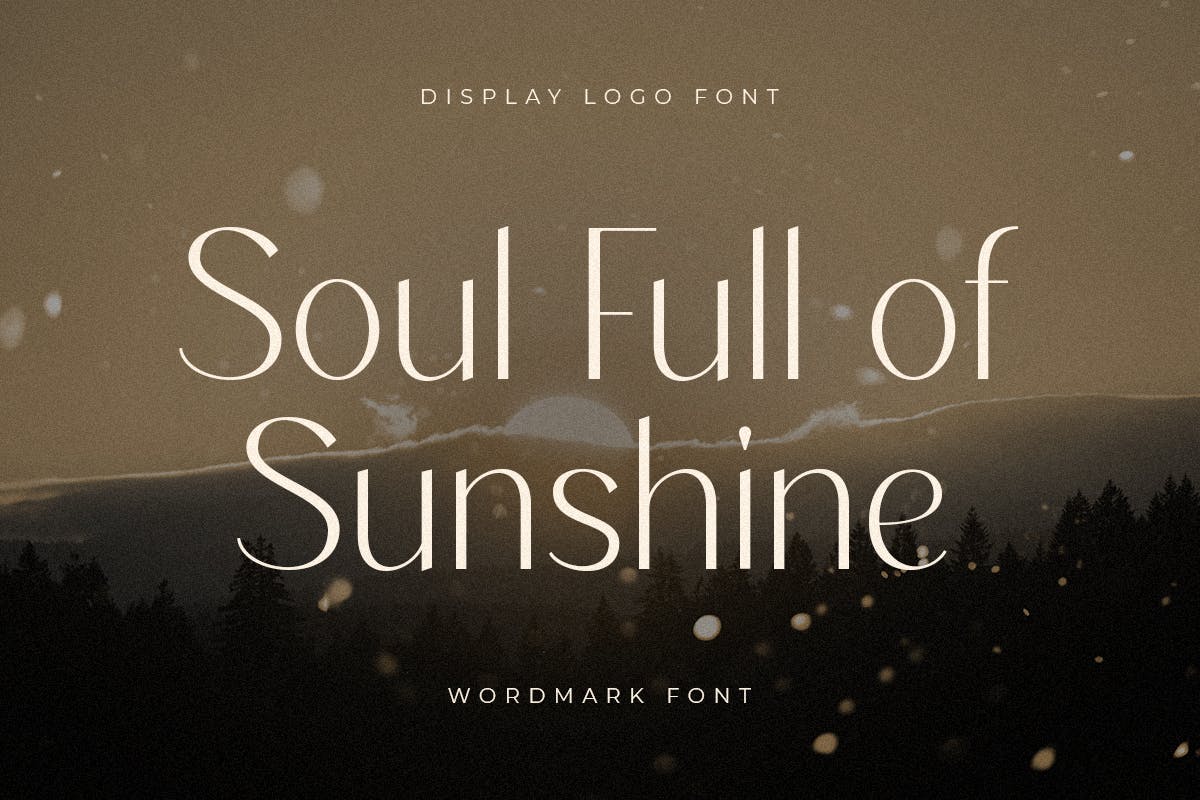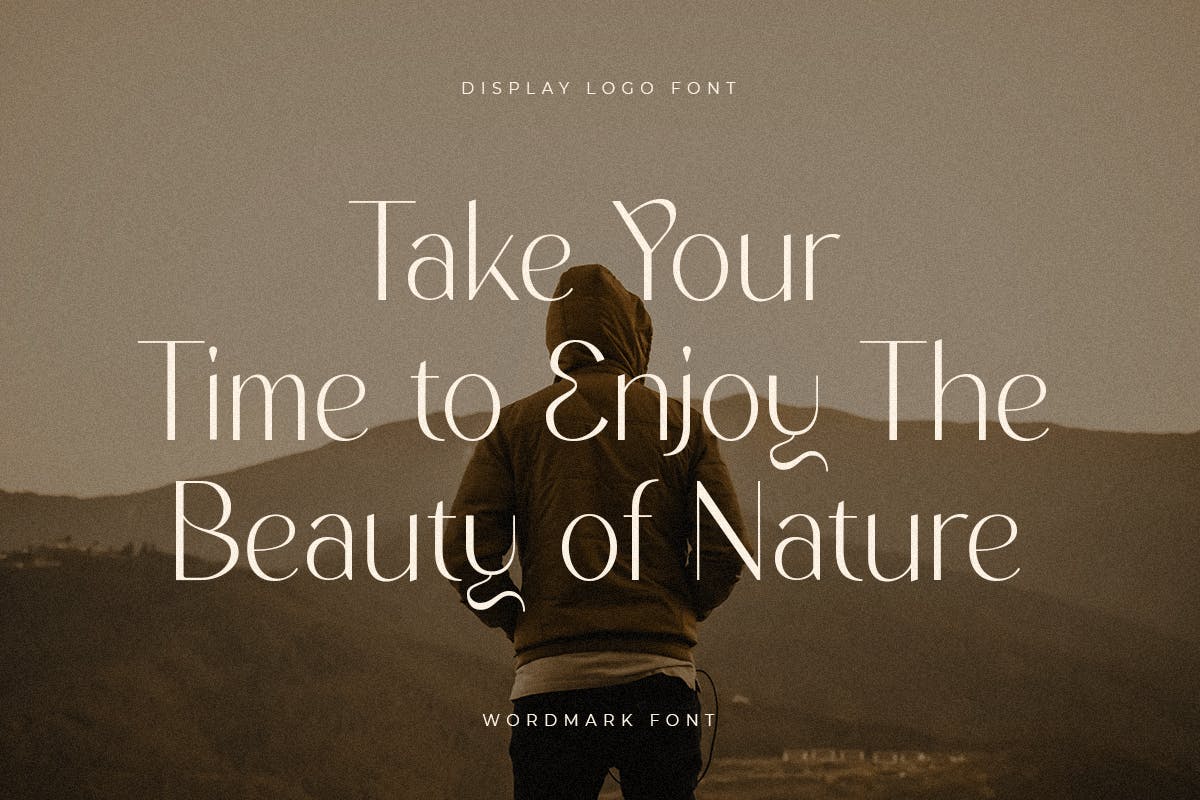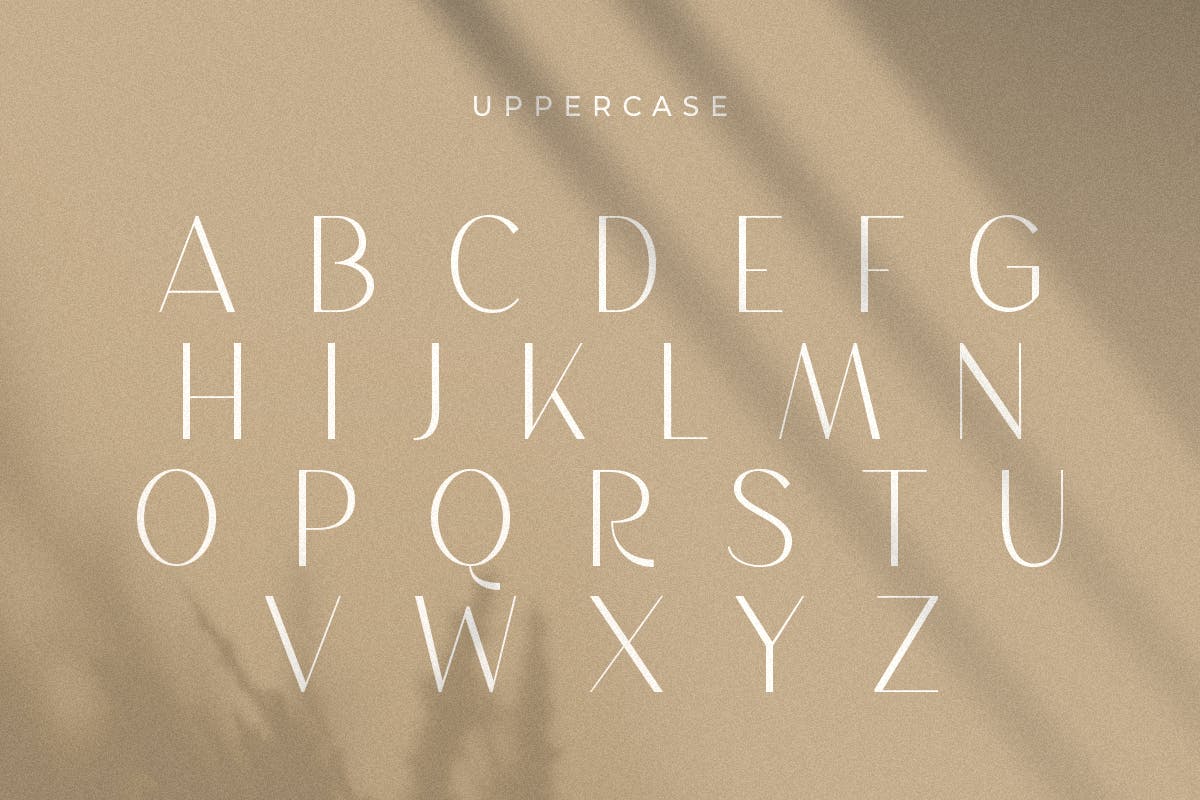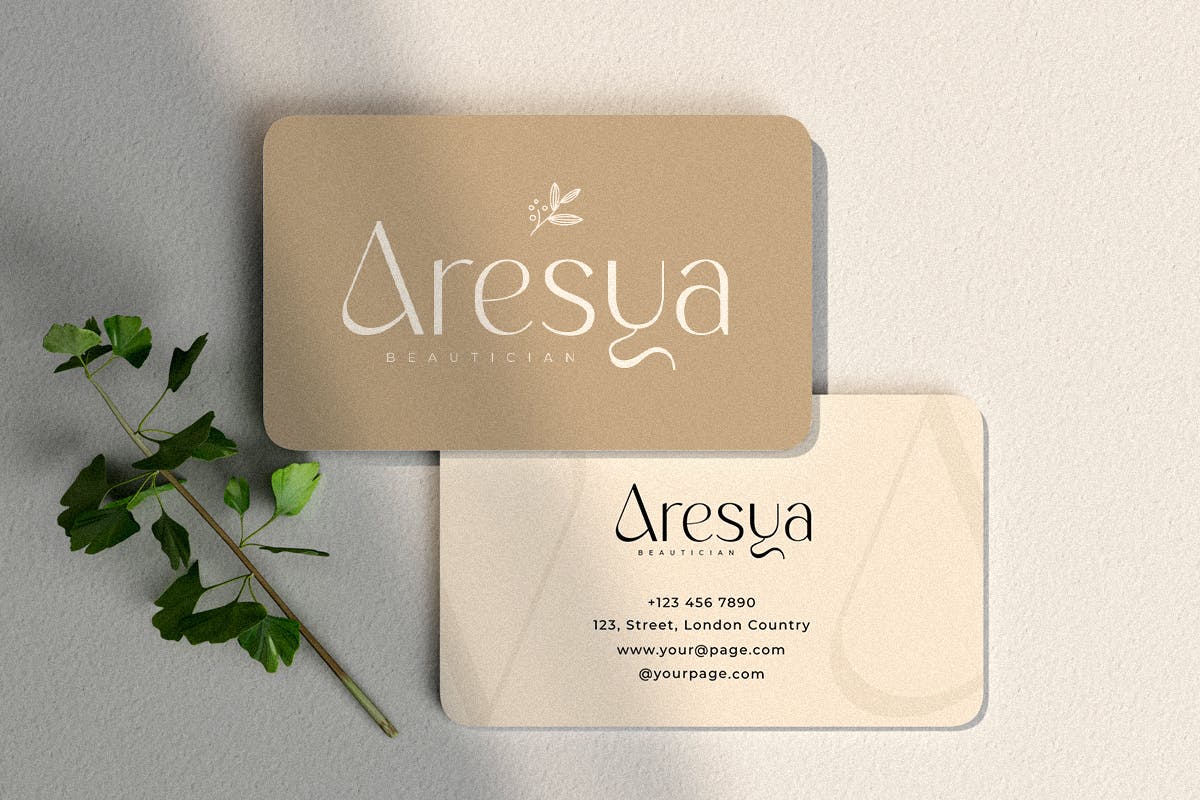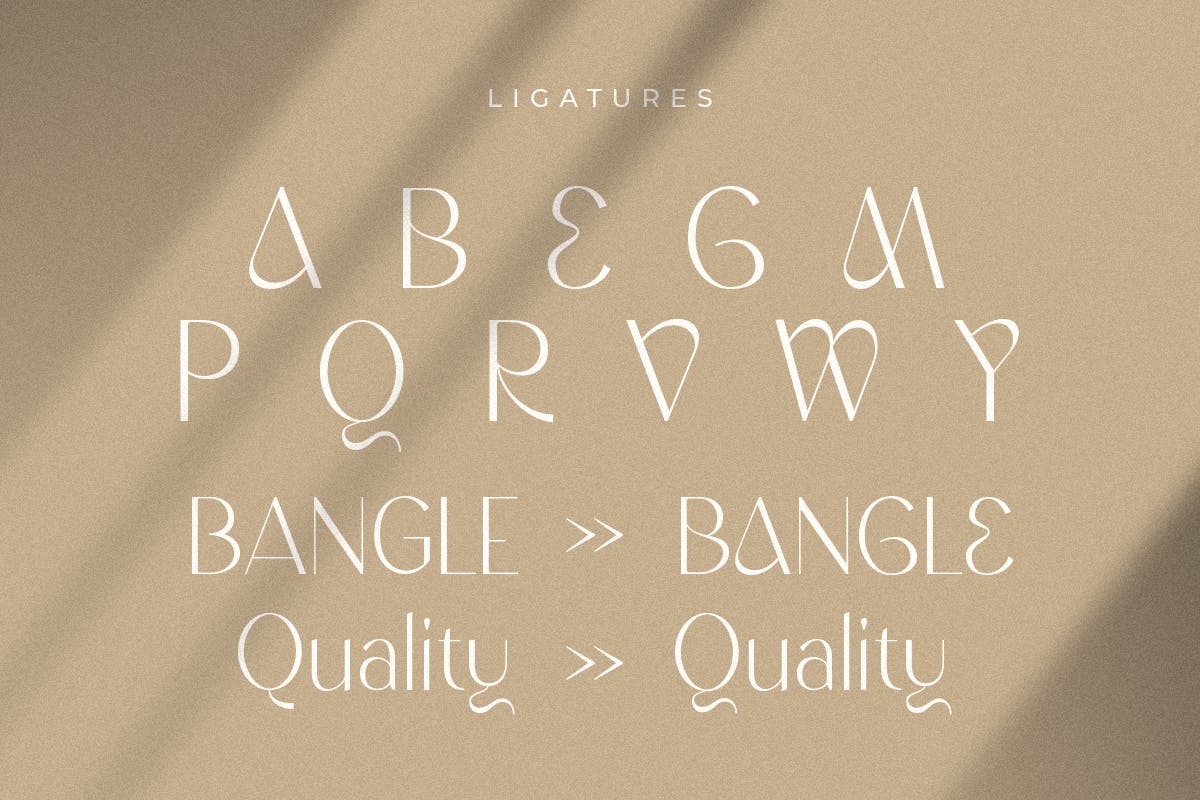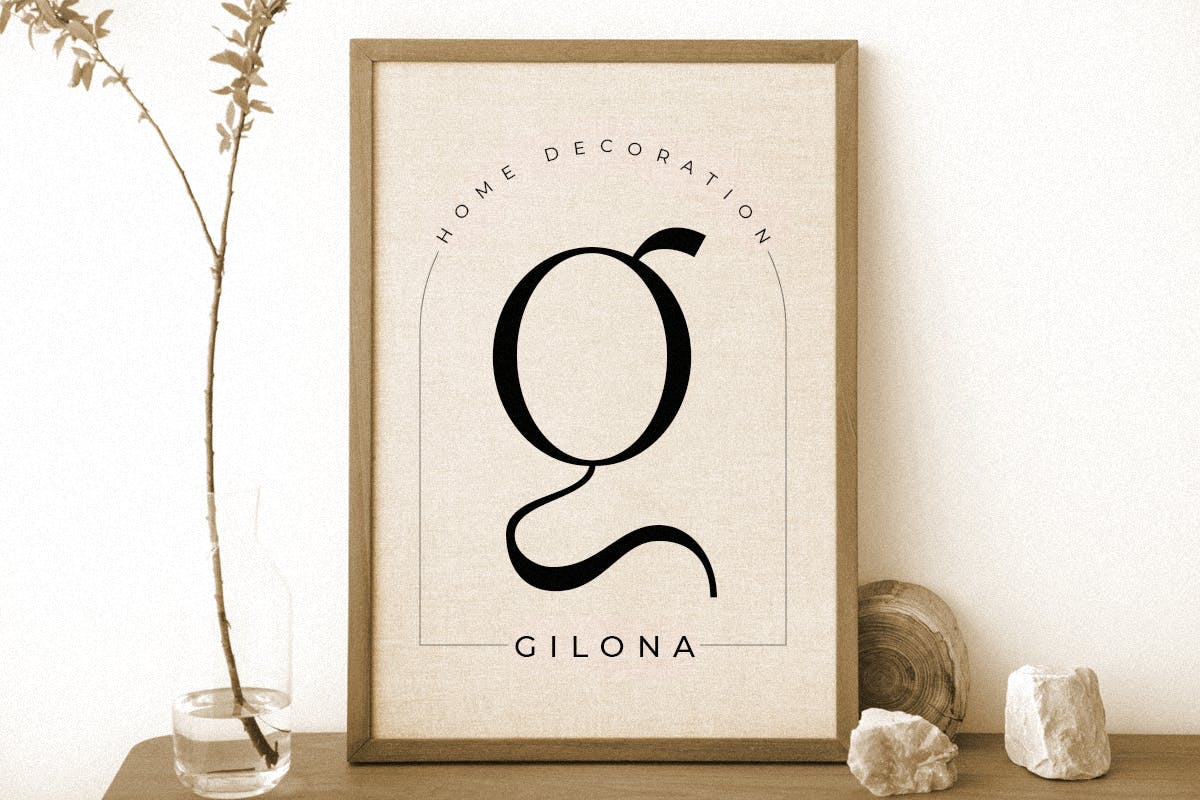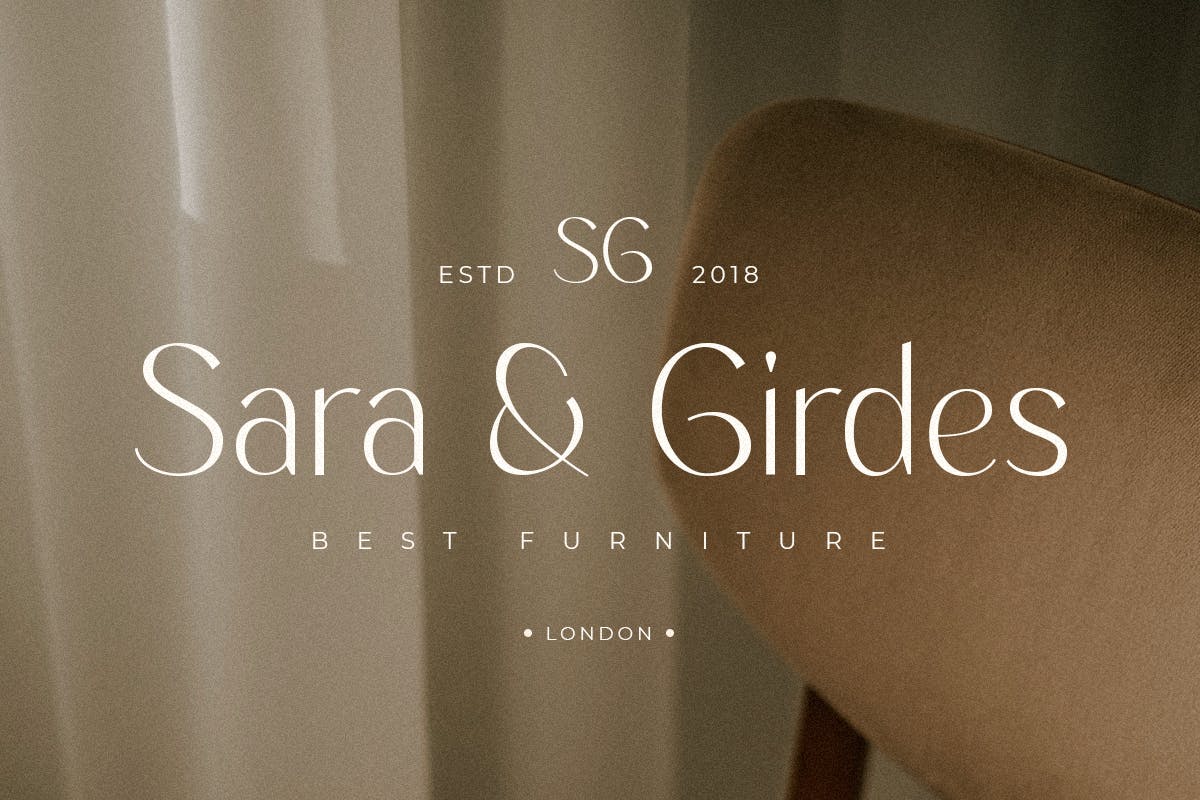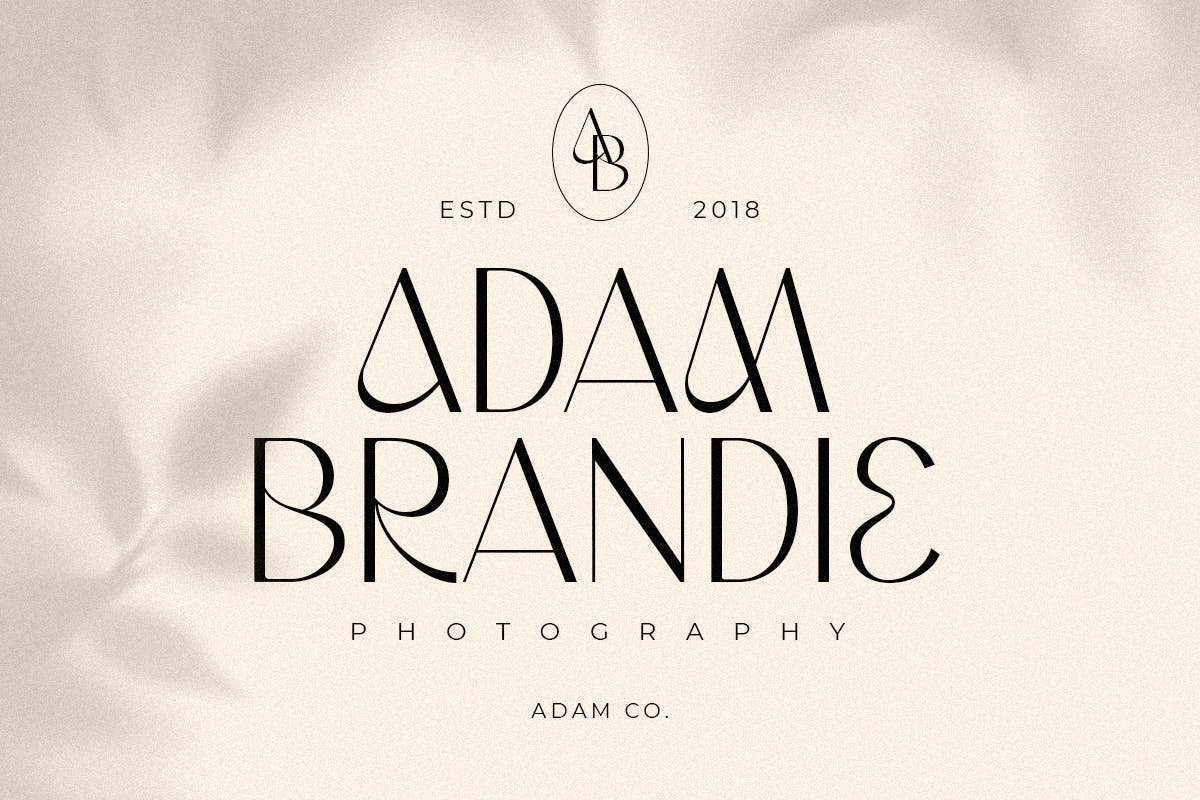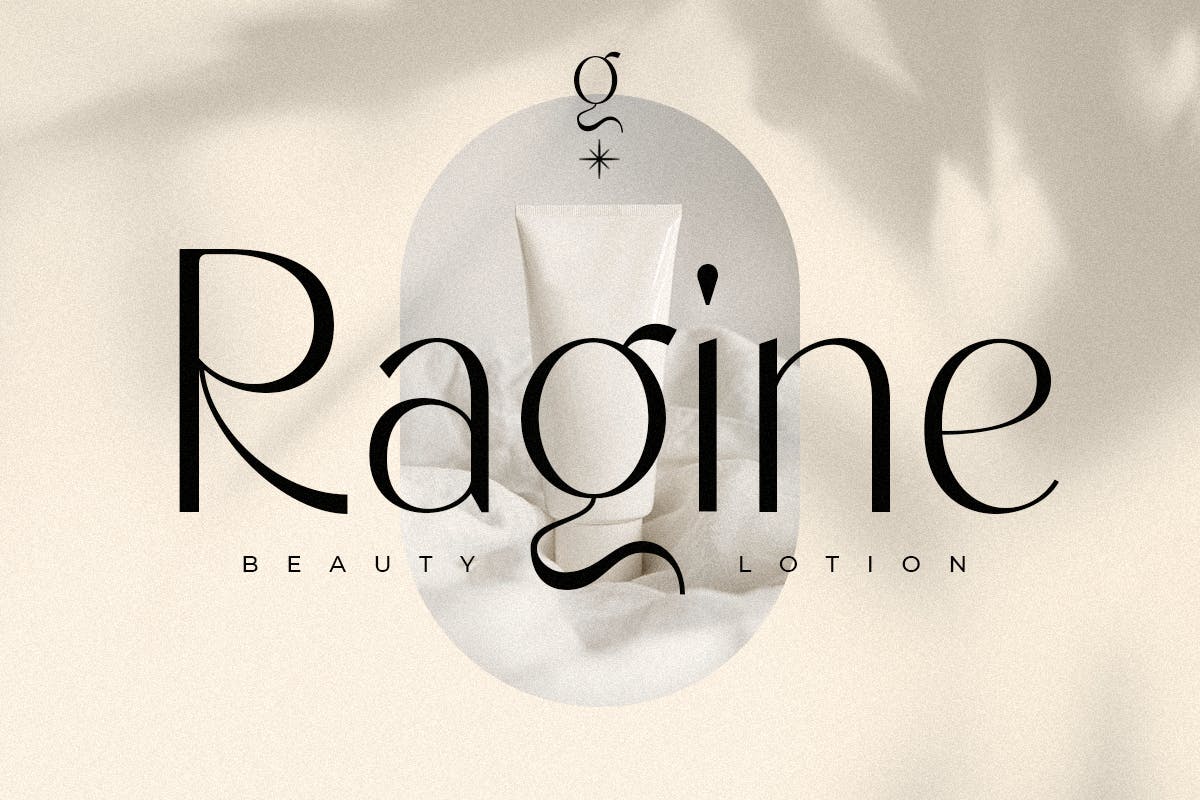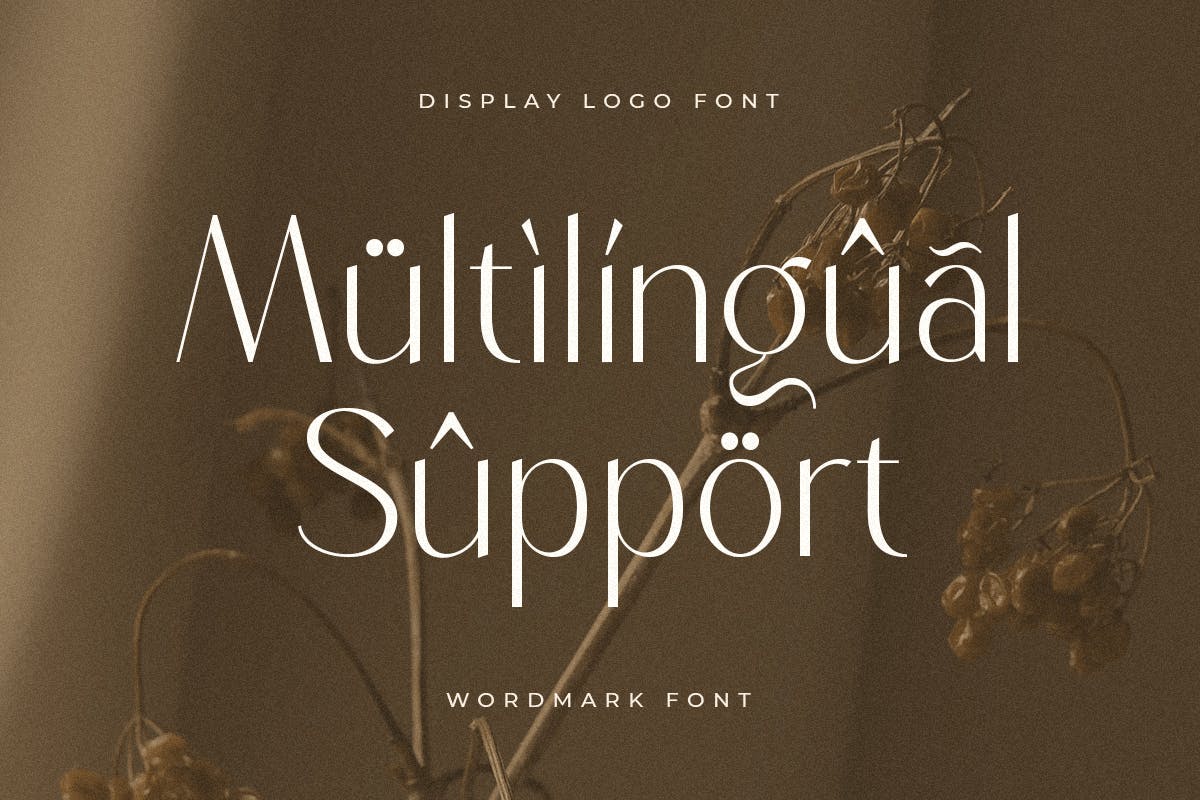
فونت لوگو وردمارک یک فونت نمایشی منحصر به فرد است که بهطور خاص برای نیازهای برندسازی زیبا و مدرن طراحی شده است. این فونت با اشکال خاص و منحصر به فرد خود، ظاهری شیک و جذاب به برند شما میبخشد. این فونت به طراحان و صاحبان محصولات کمک میکند تا طراحیهای خود را زیباتر و مدرنتر جلوه دهند. بهخصوص برای این فونت، ما کاراکترهای جایگزین متعددی تهیه کردهایم تا شما بتوانید واریاسیونهای نامحدودی برای نیازهای خلاقانه خود ایجاد کنید.